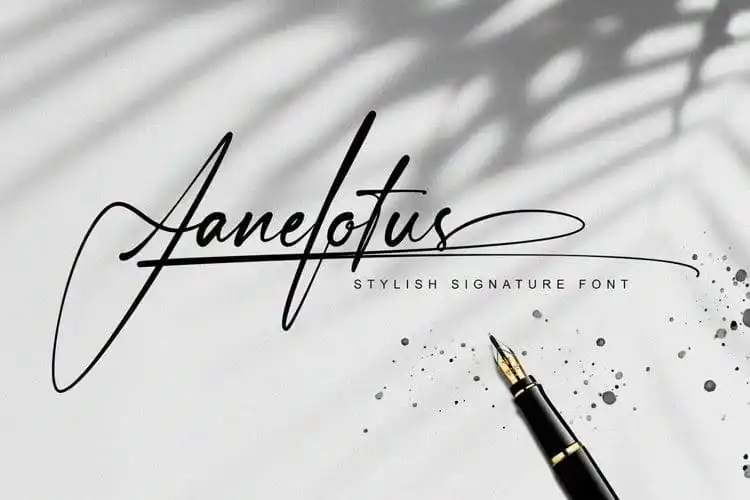
Janelotus Handwritten Font – Download Grátis
A Janelotus Handwritten Font é uma elegante tipografia script moderna projetada para imitar escrita feita à mão, capturando todos os seus detalhes e beleza única. Este tipo de letra é perfeito para uma variedade de projetos que necessitam de um ar charmoso e sofisticado, como logotipos e identidade visual, convites, embalagens personalizadas para casamentos, posts em redes sociais, anúncios e embalagens de produtos. Seu estilo é suave e descontraído, criando um enfoque elegante sobre qualquer design. Janelotus se destaca por sua simplicidade aparente, mas ao mesmo tempo por suas peculiaridades que tornam cada palavra única. É uma opção perfeita para aqueles que buscam adicionar um toque agradável e charmoso a seus projetos digitais ou físicos. Não importa o tipo de projeto, a Janelotus Handwritten Font tem sua cara e irá certamente chamar atenção. Esta fonte foi criada pelo font designer lemonthe, que oferece uma linguagem elegante e sofisticada sem perder a essência delicada da escrita à mão. Ela é perfeita para qualquer tipo de projeto, seja para criar um design personalizado ou incorporar em projetos práticos como embalagens de produtos. Janelotus também faz um excelente trabalho para aqueles que desejam adicionar um toque especial a suas mensagens online, tais como posts nas redes sociais e publicações de mídia social. Seja você designer gráfico ou amante de design, o Janelotus Handwritten Font é uma opção indispensável na sua ferramenta de trabalho. Seu estilo único e sua capacidade de adaptar-se a vários tipos de projetos o tornam uma escolha segura para quem busca um touch especial em suas criações digitais ou impressas.